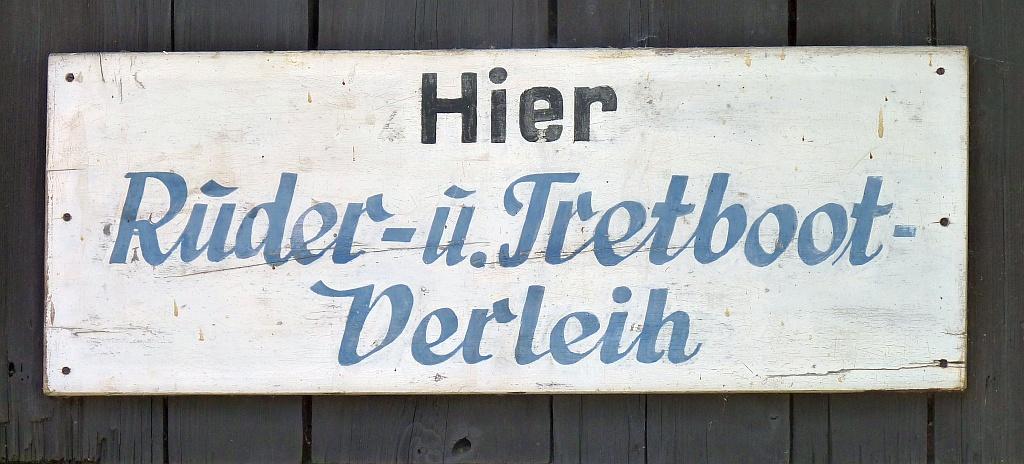
Suche Schriftart des Schildes "Ruder- u. Tretboot-Verleih" am Kochelsee
Im Sommerurlaub entdeckte ich diese wunderschöne Tafel eines Ruder- und Tretbootverleihs in Kochel am See.
Welche Schriftart ist das? In welcher Epoche war diese Schriftart üblich?
Zeitlich dürfte das Schild in die erste Hälfte des 20. Jahrhunderts fallen. Die untere ist eine typische Schildermaler-Schreibschrift ...
Handgepinselt. Schnitzel* könnte vermutlich helfen.
Die obere eigentlich auch. Durch Drehung des Breitpinsels entstehen die sehr gleichen Strichbreiten. Beim Zeichnen würde man da wohl eher drauf eingehen, bzw. wurden Satzschriften da genauer gezeichnet.
Viele Schriften in der Art (wie die untere) gibt es nicht. Guck mal hier*:
Auch die Forelle kommt aus der Richtung.
Schreiben könnte man sowas natürlich auch – wenn man es denn nicht digital braucht …
* Weiß irgendwer was über die Zierfische? Die ist ja schon länger nicht mehr erhältlich und würde hier auch passen :-?
Bzw. die Mitte? Meine Mutter wurde 1950 eingeschult und schreibt ihre Minuskel-Us mit solch einem Bogen. Ihre Handschrift erinnert generell an die gezeigte Schrift.
Meine Oma geb. 1910 schrieb das u ebenfalls mit solch einem Bogen.
Wenn ich mich recht erinnere, diente (bei Handschrift) der Bogen über dem kleinen »u« der Unterscheidung zum »n«. Meine Oma schrieb so, meine Mutter, meine Tante etc.
Das »u« mit Strich kenne ich aus Kurrent und Sütterlin … das deckt sich ja dann mit deinen Erfahrungen. Ob der Ursprung auch dort liegt weiß ich allerdings nicht.
Wie Klaus schon schrieb, musste in der Kurrent- und Sütterlinschrift das u mit Bogen geschrieben werden, um es vom n zu unterscheiden. Kann es sein, dass beim Wechsel zur lateinischen Schrift diese Eigenart einfach weiter gelehrt wurde? In der Generation meiner Eltern (Jg. 1930 bis 1940) schreiben auch die das u mit Bogen, die Sütterlin nicht mehr gelernt hatten.
Vielleicht das oder es wurde einfach übernommen, weil man es ständig so gesehen hat :-?
Ich schreibe auch so, auch wenn mein Vater und meine Mutter so nicht schrieben. Warum, weiß ich nicht, aber so konnte ich zumindest bei meiner Sauklaue n und u immer auseinanderhalten.